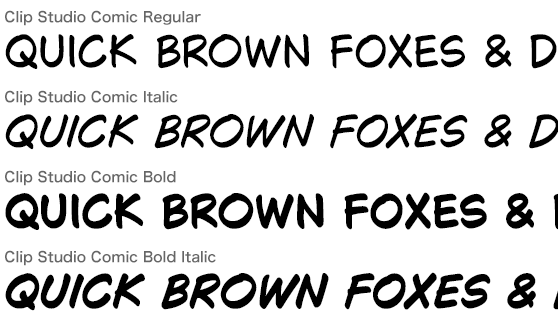
欧文手書き
株式会社イワタ
Clip Studio Comic 4書体セット (CLIP STUDIO PAINT Ver.3.00 以降搭載版)
株式会社イワタが株式会社セルシスと共同で開発し、イラスト・マンガ・Webtoon・アニメーション制作ソフト「CLI P STUDIO PAINT」に搭載されている欧文フォント「Clip Studio Comic」の4書体セット。「CLIP STUDIO PAINT Ver.3.0」以降搭載版と同一です。
よりリアルな手書き感を表現するために、1つの文字に複数のデザインを用意し、それらをランダムで表示させる処理も実装し、手書き文字ならではの揺らぎ再現しています。